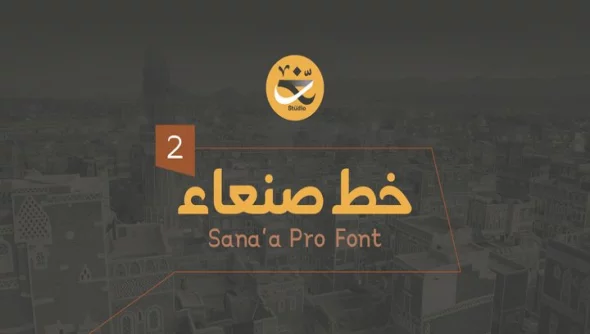
حول مجموعة خطوط صنعاء برو V2
خط صنعاء هو الإصدار الثاني من عائلة Font. إنه خط عربي ولاتيني واللغات المنقسمة عنهما. يحتوي على العديد من الأحرف والعلامات واللغات.
تتميز بتفردها في الرسم والشكل لتلبية الاحتياجات